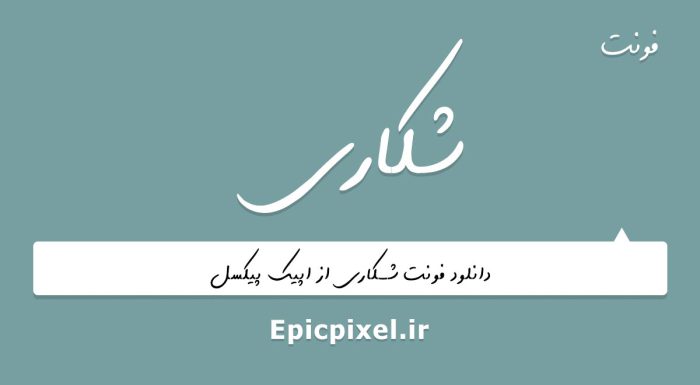
3 فونت شکاری فارسی
| ⭐ مجموعه فونت | فونت بی شکاری دست نویس Font B Shekari فونت آ شکاری بولد Font A Shekari فونت دیما شکاری ایفون Font Dima Shekari |